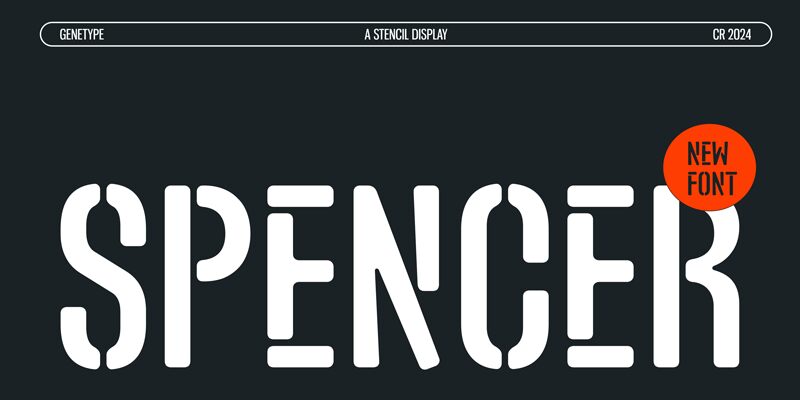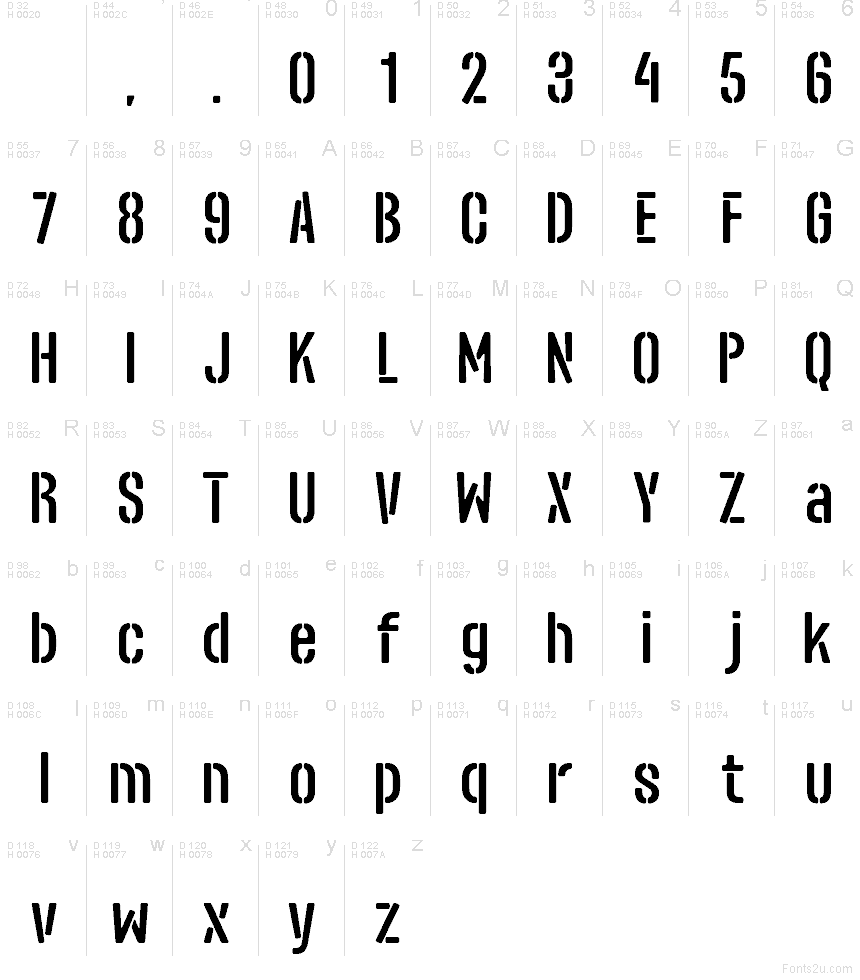
Spencer Regular
Spencer, créée par Genetype, est une police d'affichage militaire gratuite aux caractères hauts et étroits, ponctués de découpes qui confèrent aux formes un rythme façon pochoir. Le dessin est rigide et structuré, avec des terminaisons arrondies et des coupes verticales tranchantes qui maintiennent l'ensemble net et direct.
Spencer est idéale pour des affiches militaires, du branding tactique, des titres de jeux vidéo, des écussons, des étiquettes d'uniformes ou de la signalétique événementielle, car sa construction segmentée évoque une esthétique disciplinée, typique du terrain. Cette police gratuite est également parfaite pour souligner une affiche ou un logo lorsque vous recherchez un lettrage structuré et thématique, sans perdre son impact graphique.